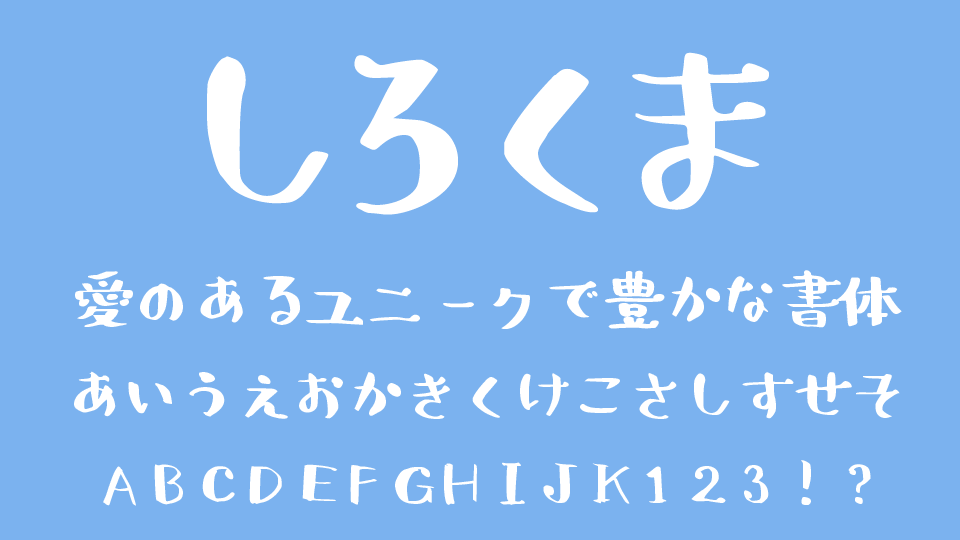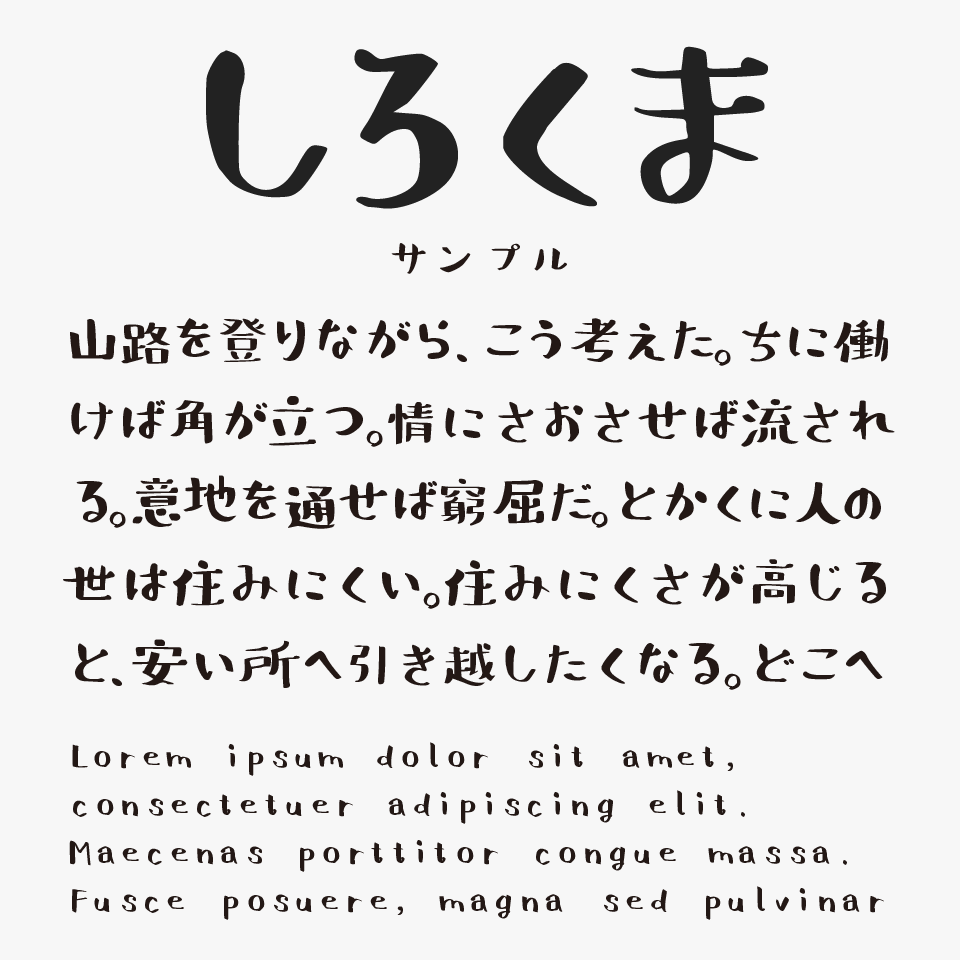
しろくまフォント
しろくまフォントは、「しろくまの肉球」をイメージして制作されたとっても可愛らしい手書きフォントです。
線幅がランダムにふっくらしていたりスラッと細かったりするところが肉球感があるデザインです。他にはないゆるくてラフなフォルムが可愛く、独特な雰囲気をもつフォントです。
しろくまフォントは、サインペンか筆ペンかで書かれたような不揃いで可愛らしい独特な線の太さがとっても素敵で、このフォントが使われてるデザインを見ると少し嬉しくなります。
普段と少し違った手書き文字の印象を作りたい時に、キャッチコピーやタイトルデザインなどに「しろくまフォント」はオススメです!